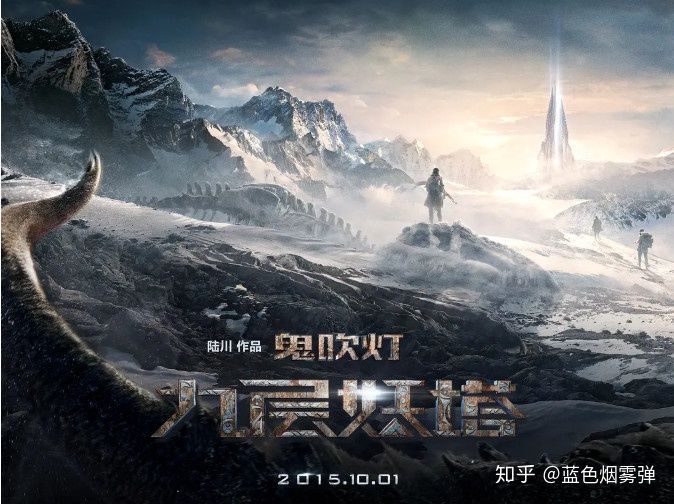
解决字体侵权问题,三招帮你搞定
作为设计师,我们在设计的时候需要使用各种各样的字体,你肯定非常头疼字体版权的问题,而且这几年越来越频繁。
随着知识产权相关法律的完善和版权保护意识的提升,关于字体侵权的纠纷时有发生。
2007年,方正起诉暴雪字体侵权并索赔1亿元,2009年索赔金额被追加至4.08亿元,2012年,最高人民法院判决暴雪公司等停止侵权并赔偿北大方正公司经济损失200万元及诉讼合理支出5万元。
2008年,方正起诉广州宝洁因其飘柔等产品包装上使用了倩体字,并索赔134万元,但最终败诉。
2012年,热门影片《失恋33天》,因片头字幕、短信字幕等使用了未授权字体,最终赔付版权方2万元。
2016年,《九层妖塔》因使用了未授权字体中的7个字,就被索赔51万元。
目前,法院对这类侵权的判决一般为一个字3000-10000元。如果字体设计在产品营利方面起到关键作用,赔偿金额还会更多。除了赔钱,已经发出的宣传品需要撤回,应对法律纠纷也需要不小的投入,企业在经济和品牌形象上都要遭受不小的损失。
事实上,侵权与维权的背后不只是利益的撕扯,还有关于创意价值认可的较量。
比如,2007年方正诉暴雪字体侵权的案子,终审判定暴雪等被告方赔偿200万元。这不但与方正的索赔金额4.08亿元相去甚远,甚至比照方正为一审、二审付出的400多万元诉讼费也差了一大截。
所以,作为字体的使用者,作为设计行业的从业者,我们更应该给与版权方应有的尊重和理解,不仅可以让字体公司和字体设计师得到应有的回报,也有利于设计和创意的价值体现,更重要的是对设计创新的鼓励和设计环境良性发展的推动。
字体侵权的哪些“坑”
版权是对计算机程序、文学著作、音乐作品、照片、电影等的复制权利的合法所有权。除非转让给另一方,版权通常被认为是属于作者的。大多数计算机程序不仅受到版权的保护,还受软件许可证的保护。版权只保护思想的表达形式,而不保护思想本身。算法、数学方法、技术或机器的设计均不在版权的保护之列。版权亦称“著作权”。
那些作品享有著作权,著作权人有哪些权利,那些行为属于侵权行为,侵权要承担什么的责任,可以搜索查阅《著作权法》的相关规定。
需要明确的是所有的字体都是有版权的,版权归属于字体厂商和个人。其中有些字体是可以无需授权、完全免费的,可以个人使用、也可以商业使用,例如Windows系统自带的属于公共版权的宋体、仿宋、黑体、楷体可以免费使用。但大多数的字体都是需要购买版权才能使用的,否则则构成侵权。
界定是否侵权需要明确两个问题,字体是否收费,是否是商业用途。
字体厂商一般都有官网和电话,可以通过网络查询该字体是否收费,个人设计者可以通过搜索微博或者公众号等自媒体渠道查询是否收费。
360推出了360查字体的工具,可以一键检测电脑安装字体是否免费或是“商用需授权”的,非常的方便使用,大家可以试试,工具地址:fonts.safe.360.cn/。目前功能还在完善中,不是所有的字体都能查到。
判断是否是商业用途,除了查阅《著作权法》外,主要看是否以直接营利或者间接营利为目的。
但有个经常遇到的坑需要特别注意。
在多起涉及著作权的纠纷中,被吐槽最多的是微软雅黑。微软雅黑作为Windows操作系统的内嵌字体,实际上,“微软雅黑”是由“北大方正电子有限公司”设计开发的字体作品,方正公司通过协议的形式授权微软公司使用。虽然可在微软系统内使用,但其实版权已在微软公司进入中国,归了北大方正所有。而用户如果在非Windows操作上显示以及打印,均涉及版权,需要维持支付一定的版权费。前段时间的疯传网络的“微软雅黑字体商用侵权,公司被索赔千万”的事件”正是踩了这个坑。
我们仅可以在Windows系统中使用微软雅黑,脱离Windows平台的一切商业行为,都属于侵权行为。所以当查看的载体为微软 office 软件时,不涉及字体侵权。但是,使用PDF查看、作为图片使用、或者印刷出来使用,就涉及到字体侵权。
在网页前端代码里,在 css 样式文件中,如果字体样式以引用的方式则不侵权,但是如果预加载微软雅黑字体样式,则构成了侵权。
如何更好的解决字体侵权问题呢?
第一招,创造新字体
一般在日常工作中,很少需要创造整个字库。如果需要创造整个字库的需求,一般会需要一个专业的设计团队去做。通常,在广告图片、海报、标志中,很多场景下的标题字体需要设计。作为标题,字数不会太多,我们完全可以创造出一款新的字体,当然,也有一种捷径,延用一些已有的字体的框架,通过增、删、改、修,使其无论从结构、风格、笔画都有一个非常大的改进,更快的去创造出新的字体。
如何确定变形后的字体是否对原来的字体侵权呢?判断依据为文字变形幅度是否超过 50%,我也专门咨询过公司的法务,他建议应该超过70%,法律上也没有明确的规定,需要具体情况具体分析,总之,变形幅度越大、风险越低。
汉字是世界上最古老的文字之一,已有六千多年的历史,中国文化最具代表性的符号,是中华民族重要的精神文化财富。从甲骨文、金文、籀文、小篆,至隶书、草书、楷书、行书,再到为印刷而设计的宋体、仿宋、楷体、黑体等,而书法更是将汉字上升到一种独特的艺术,兰亭序和祭侄文稿更是成为无价之宝。
创造字体不仅可以让你的作品独一无二,更是传承发展中国文化,提升艺术审美的最好的方式。
据统计,汉字字体库有850多款,与英文50000多款的字体库数量差距甚远。
2006年,“中华字库”工程被列入《国家“十一五”时期文化发展规划纲要》的重大建设项目,并于2009年被列入国家《文化产业振兴规划》。
“中华字库”工程是引领中华文化步入信息化、数字化时代的先导性、奠基性工程,目的是要“建立全部汉字及少数民族文字的编码和主要字体字符库。重点研发汉字的编码体系、输入、输出、存储、传输以及兼容等关键技术”。完成后的“中华字库”,预计可编码字符数在50万左右(汉字古文字约10万、楷书汉字约30万、各少数民族文字约10万),力争达到能对我国所有的出土、传世文献和当代文字作品进行数字化处理,全面打通信息化的发展瓶颈,使中华各民族文字的使用,中华文明的普及与传播,更加方便和高效。
第二招,为字库付费
很多人觉得字库太贵,实在买不起,其实不只是钱的问题,还是设计意识和价值的问题。设计一款字体库,每个笔画每个部件都需要精心设计和调整,非常耗时耗力,字库产品的价格,是和字体公司的人力财力付出成正比的。
一个字库少则需要五六千字,多的能达到一两万字,每个字都需要设计师一笔一画地仔细勾勒、调整,通常设计一套风格字库需要设计1万左右的字符+标点符号,几个人的团队少则半年,多则两三年才能开发出来。当年微软公司斥巨资委托方正字体公司专门为Vista系统设计制作的字体“微软雅黑”,平均一个字设计费用要100美金。
而漫长的开发过程和昂贵的开发费用必须要依赖于后期的大量销售,一款字体才能赚钱。
中国网民逐渐习惯了听歌要钱,看剧、看综艺、看漫画要钱,用迅雷下载出现“应版权方要求,该资源禁止下载”的情况也越来越多。和吃饭穿衣要付费一样,字库作为商品也必须要付费。
付费更能刺激字体公司和设计团队产出高质量的字体,同样的使用之后设计出来的广告、海报等作品也会更优秀。
第三招,使用免费商用字体
一些伟大的公司和无私的设计师,把自己辛辛苦苦设计出来的字体拿出来,免费的供大家使用。我们在无偿使用的同时,应该给他们的开放分享精神致以最大的尊敬。
大名鼎鼎的思源字体由 Adobe 在线字体库 Typekityu 与谷歌一起合作开发,字库对中(简体/繁体)、日、韩三国汉字进行了全面优化支持,可以说是非常全面了,其实思源不仅是个免费字体,还是一个开源字体,任何用户都可以在思源的基础上调整修改出新字体。
站酷作为中国人气设计师互动平台,不仅聚集了百万优秀设计师,也分享了多款免费字体可供商用。站酷高端黑便是站酷网近百名设计师参与创作开发的。